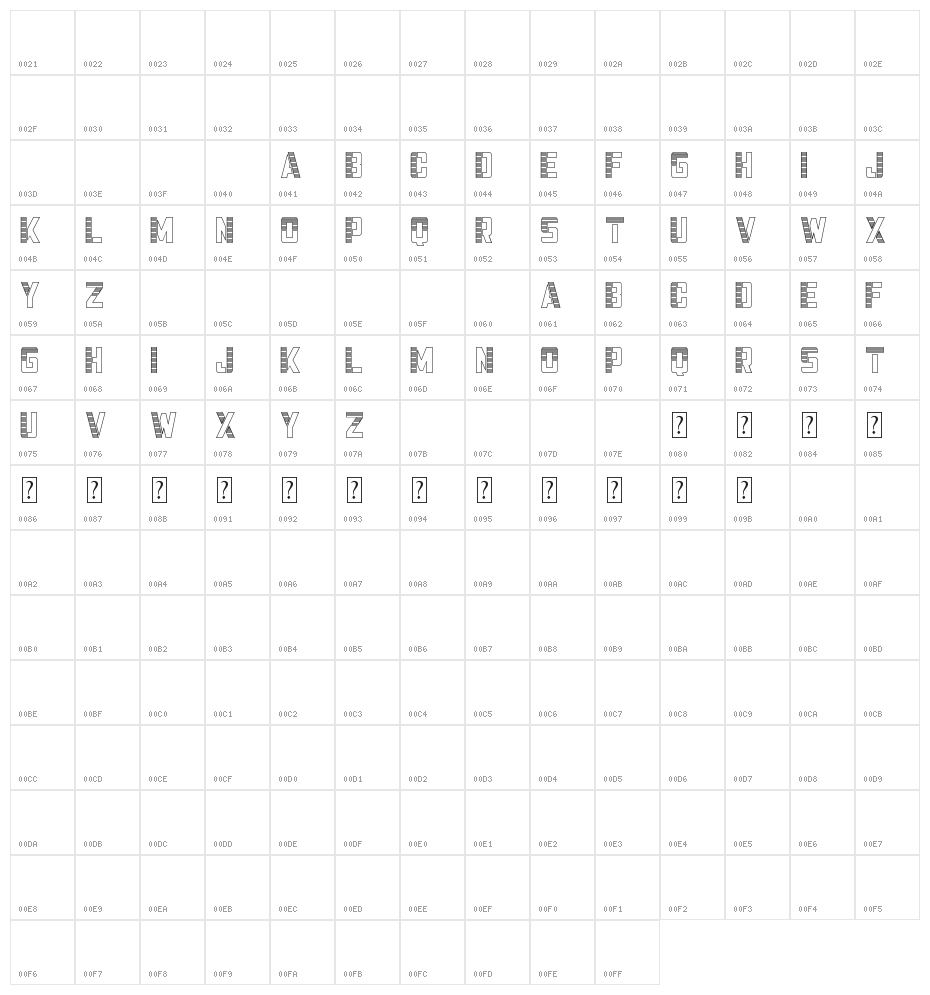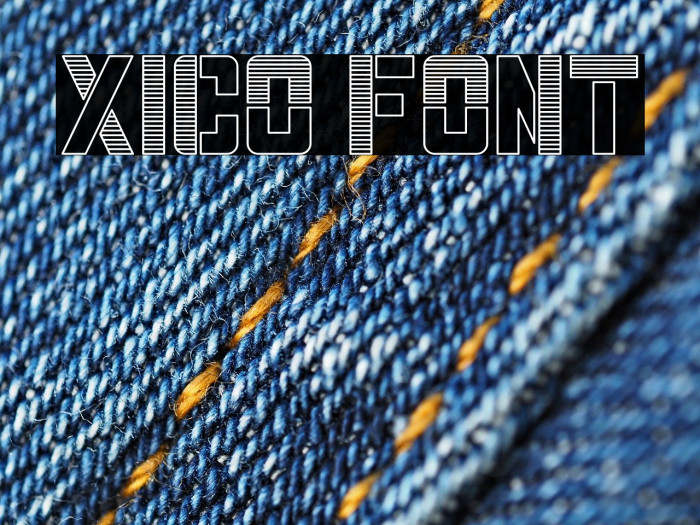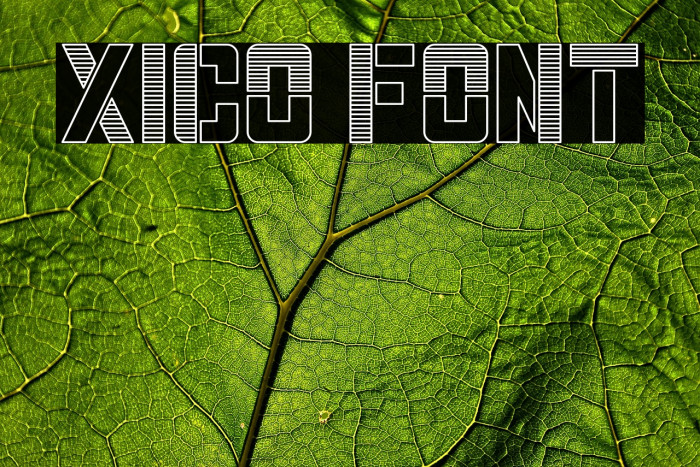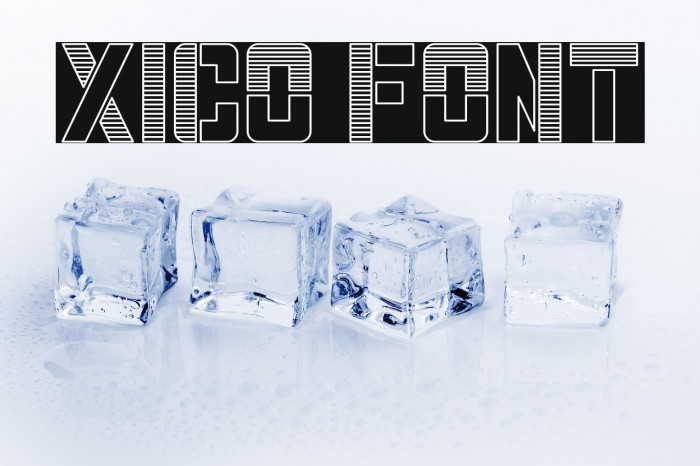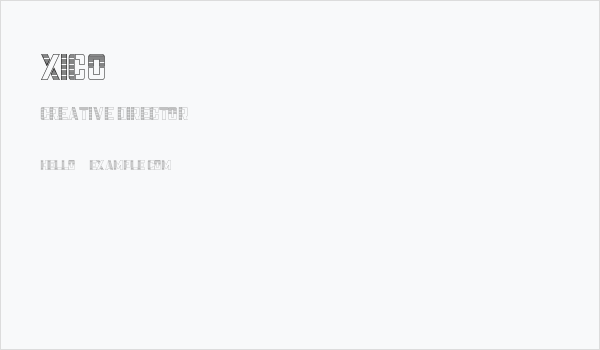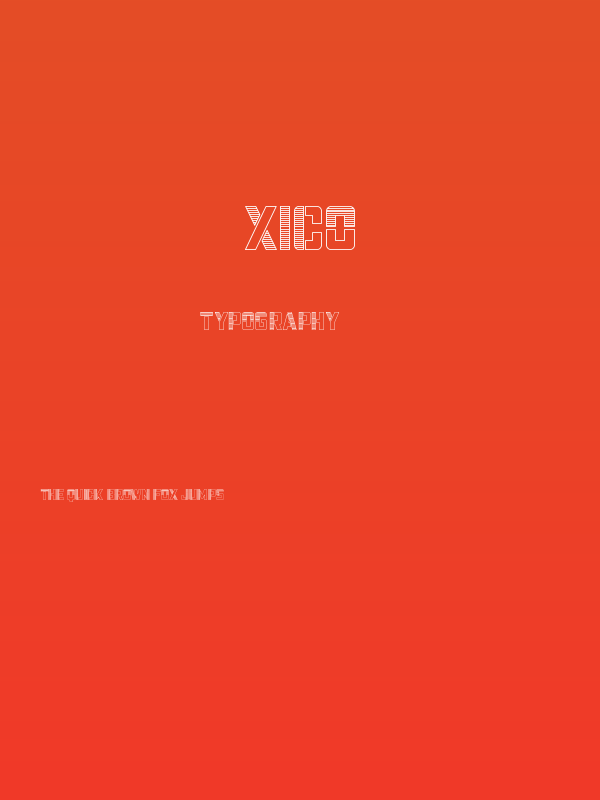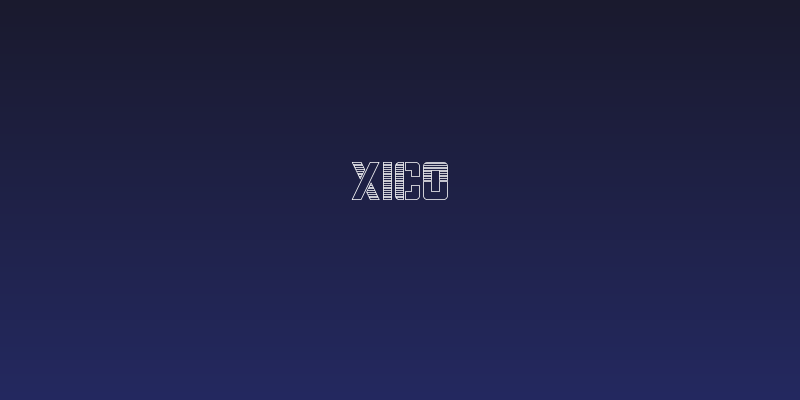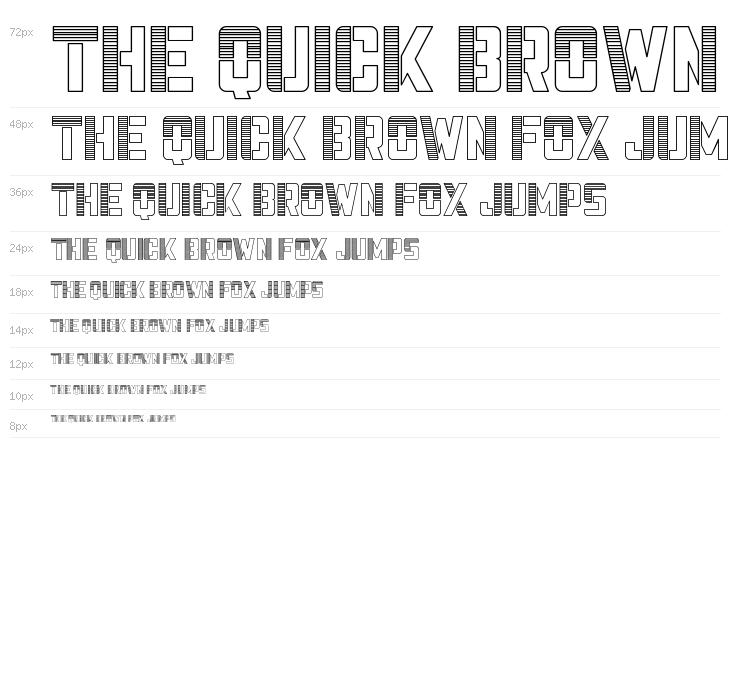
Xico Font
| Progetti proposti | This font is perfect for projects that require a strong visual impact, such as posters, logos, and branding materials. Its distinctive style makes it suitable for modern and industrial-themed designs. |